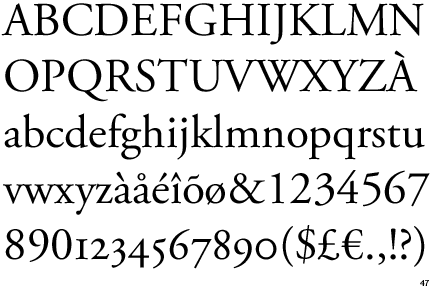
Καμιά φορά ακούμε τους πολιτικούς να αναφέρονται για περικοπές στις δαπάνες και “πάταξη της κυβερνητικής σπατάλης.” Αυτό μπορεί να είναι κάτι πολύ απλό. Ας εξηγήσουμε τι εννοούμε.
Ο Suvir Mirchandani, είναι ένας 14-χρονος από το Πίτσμπουργκ. Ο νεαρός προσπάθησε να απλώς να γλυτώσει το σχολείο του από κάποια έξοδα (και να ολοκληρώσει ένα project που του είχε ανατεθεί). Στα πλαίσια της εργασίας του ανέλυσε πολλές σημειώσεις των δασκάλων του με ένα εργαλείο που ονομάζεται APFill® Ink Coverage Software, προσπαθεί να καθορίσει ποιες γραμματοσειρές χρησιμοποιούσαν το περισσότερο μελάνι.
Κατέληξε στο συμπέρασμα ότι με την εκτύπωση εγγράφων αποκλειστικά με την γραμματοσειρά Garamond, η οποία έχει ένα ευκρινές αλλά λεπτότερο αποτύπωμα από την Times New Roman ή την Century Gothic, το σχολείο του θα μπορούσε να μειώσει την κατανάλωση μελανιού κατά 24%. Το ποσοστό δεν είναι μικρό, αφού αν το μετατρέψουμε σε δολάρια, το σχολείο θα μπορούσε να εξοικονομεί 21.000 δολάρια τον χρόνο, όπως αναφέρει το το CNN.
Εντυπωσιασμένος από τις διαπιστώσεις του μαθητή, ο δάσκαλος του τον έφερε σε επαφή με το Journal for Emerging Investigators, μια ιστοσελίδα που ιδρύθηκε από φοιτητές του Harvard, προκειμένου να δημοσιεύουν τις ακαδημαϊκές τους εργασίες. Από το Journal for Emerging Investigators, είδαν με ενδιαφέρον την έρευνα του 14-χρονου και σκέφτηκαν να επεκτείνουν το πεδίο εφαρμογής και να συμπεριλάβουν ολόκληρη την ομοσπονδιακή κυβέρνηση, η οποία χρειάζεται 1.800.000.000 δολάρια ετησίως μόνο για εκτυπώσεις.
Τα αποτελέσματα της έρευνας (“A Simple Printing Solution to Aid Deficit Reduction”) που προέκυψαν παρουσιάζουν εντυπωσιακά αποτελέσματα και εξηγούν γιατί η Ουάσιγκτον θα πρέπει να υιοθετήσει επίσημα την γραμματοσειρά Garamond σαν υποχρεωτική γραμματοσειρά της κυβέρνησης.
“Ακόμα κι αν οι δαπάνες των εκτυπώσεων έχουν μειωθεί τα τελευταία χρόνια” αναφέρει ο Mirchandani στη συνοπτική παρουσίασή του, ” συνεχίζουν να είναι υψηλές και μια αλλαγή της γραμματοσειράς μπορεί να οδηγήσει σε σημαντική εξοικονόμηση χρημάτων.”
Για πόσα χρήματα μιλάμε; “Η ανάλυση προβλέπει ότι η ετήσια εξοικονόμηση της κυβέρνησης μόνο με την αλλαγή στην Garamond είναι πιθανό να εξοικονομήσει έναν μέσο όρο 234 περίπου εκατομμυρίων δολαρίων (στη χειρότερη περίπτωση 62 εκατομμύρια δολάρια και στη καλύτερη 394 εκατ. δολάρια).”